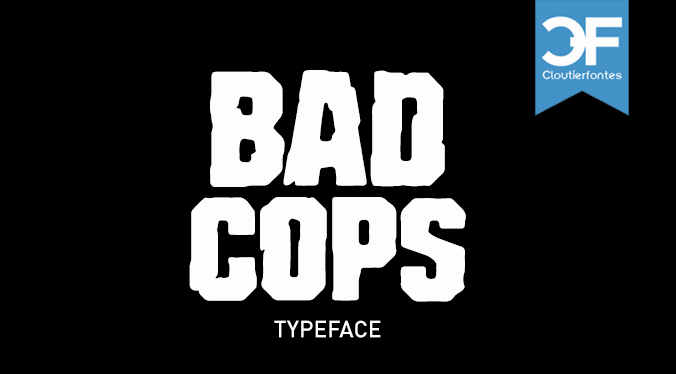
A CF Bad Cops Font é uma fonte de display que oferece um toque audacioso e carregado de personalidade para qualquer projeto visual criativo. Desenvolvida pelo designer Hamilton, essa fonte traz uma mistura única de graça e provocação, ideal para uso em logotipos, design gráfico impactante ou até mesmo em elementos visuais para redes sociais. Com seus traços definidos e um desenho arredondado que não hesita em usar cores vibrantes e tons assertivos, a CF Bad Cops é perfeita para destacar sua presença digital. Seja você uma marca inovadora ou um profissional de design buscando dar vida aos materiais de marketing com algo único e marcante – essa fonte está aqui para ajudá-lo. Não importa o uso que você faça dela, se seu objetivo for pessoal ou comercial, a CF Bad Cops oferece mais de 100 caracteres únicos à sua disposição. Se você estiver pronto para inovar na forma como seus materiais visuais são apresentados e deseja experimentar uma fonte que não mede esforços em dar vida às suas ideias, então a CF Bad Cops é definitivamente para você. Comprar um license permite-lhe ampliar ainda mais essa experiência, garantindo que a personalização de seu projeto esteja sempre na vanguarda das últimas tendências digitais.